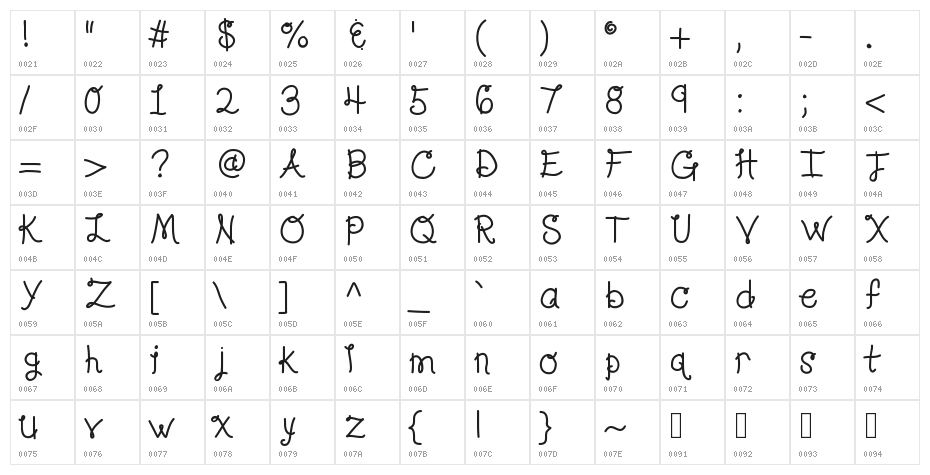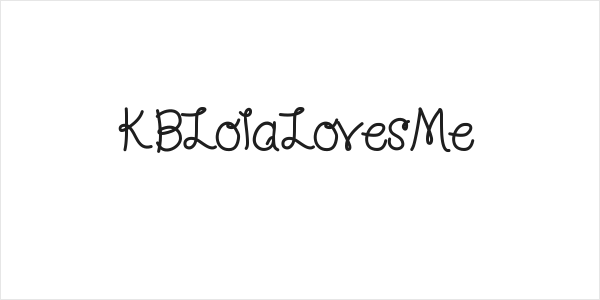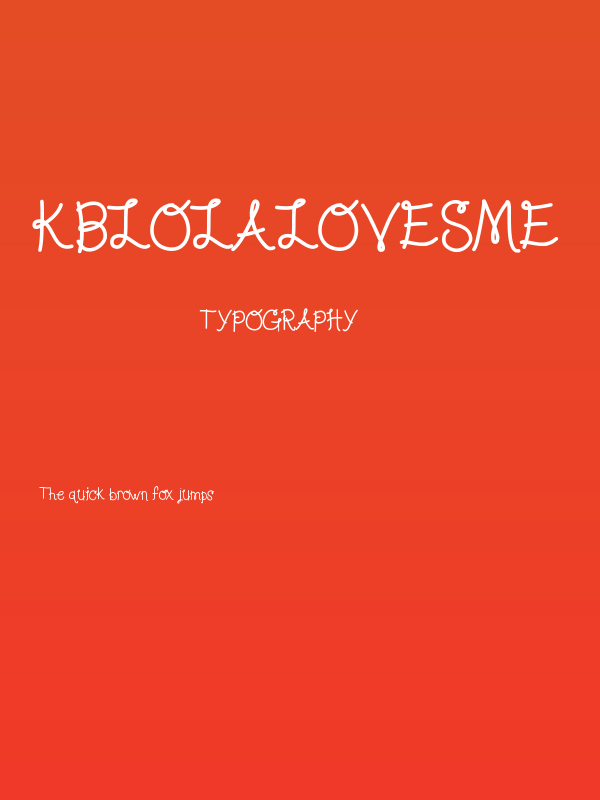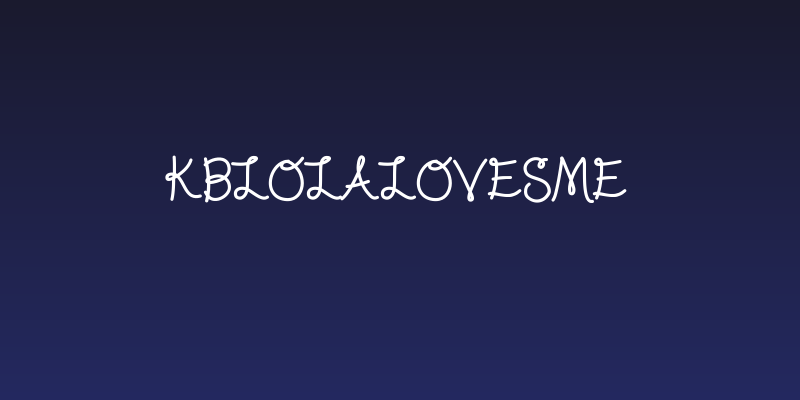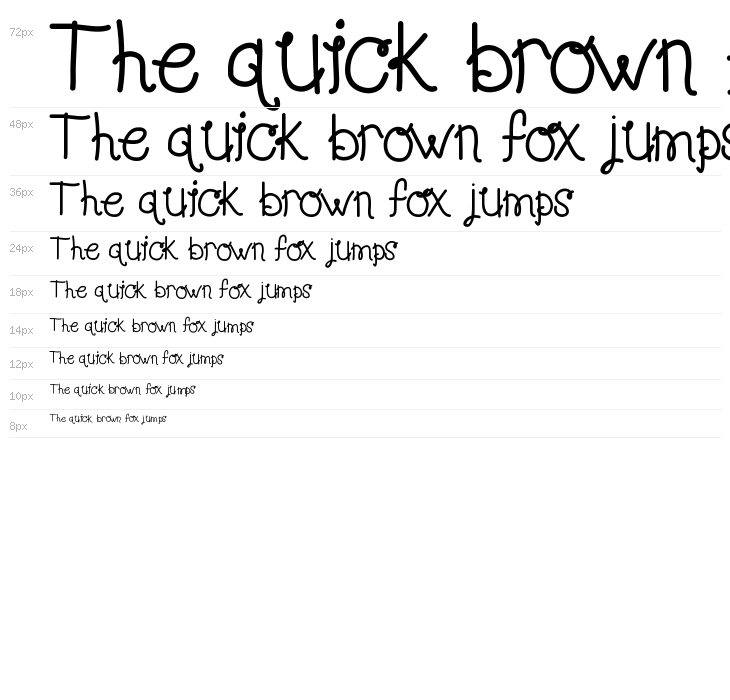
KBLolaLovesMe Font
| Gesamtstil | Playful |
| Anwendungsfall | Logos, Headlines, Greeting Cards |
| Vorgeschlagene Projekte | Ideal for children's books, greeting cards, playful branding, or any project requiring a personal, whimsical touch. |